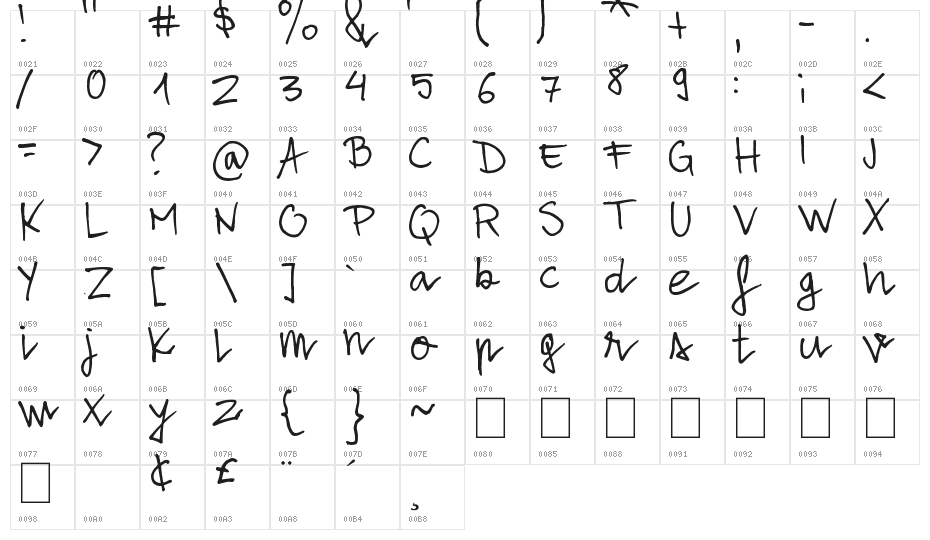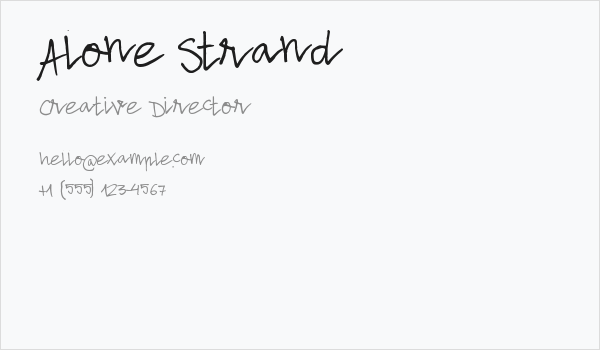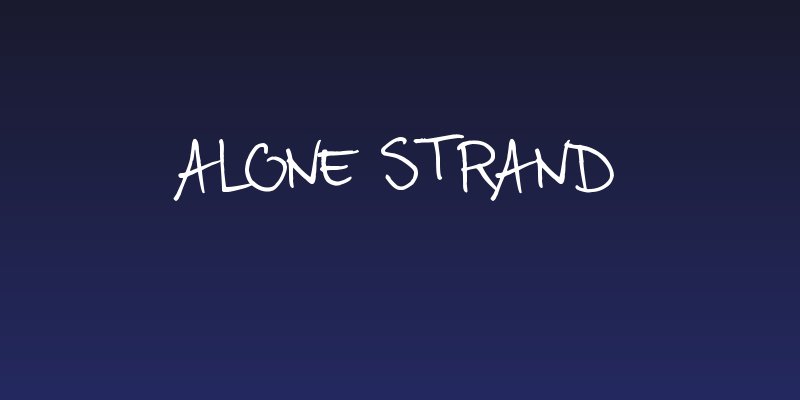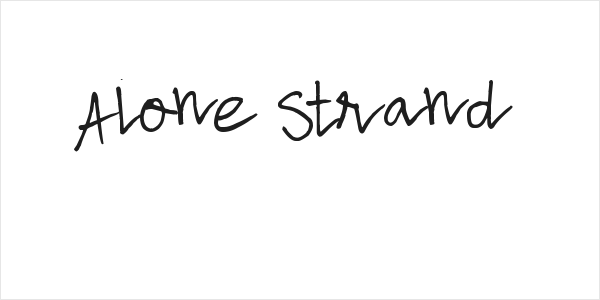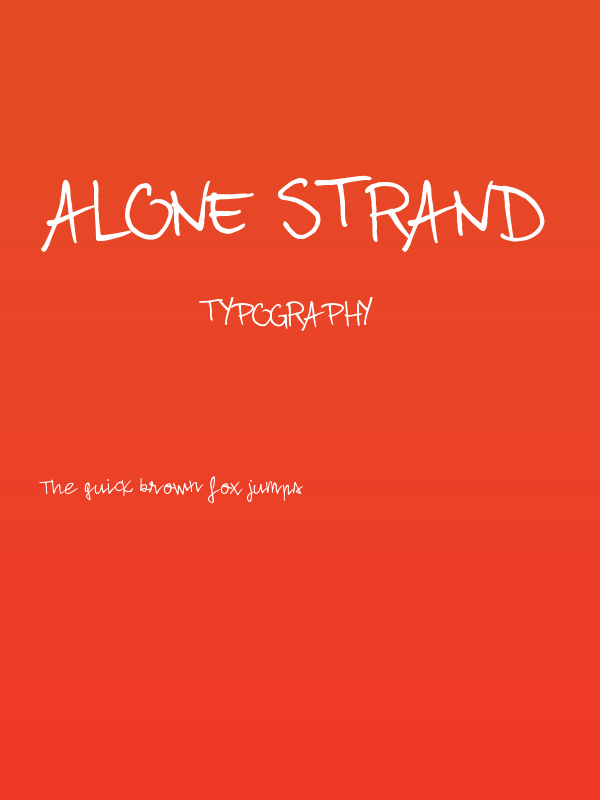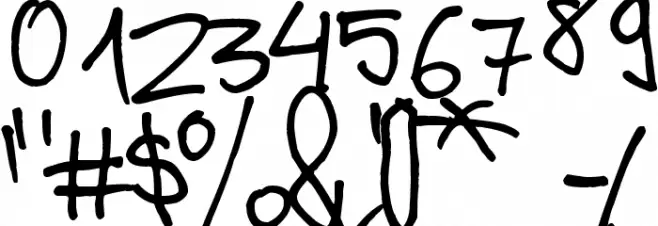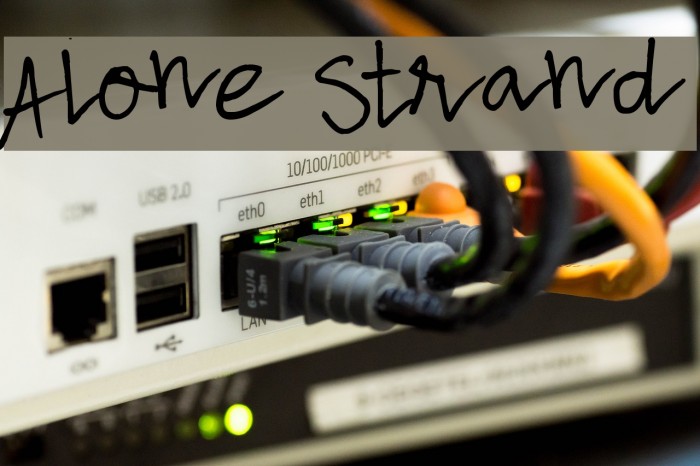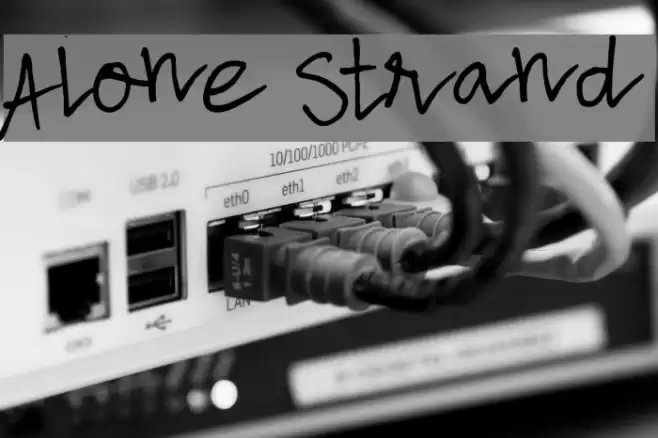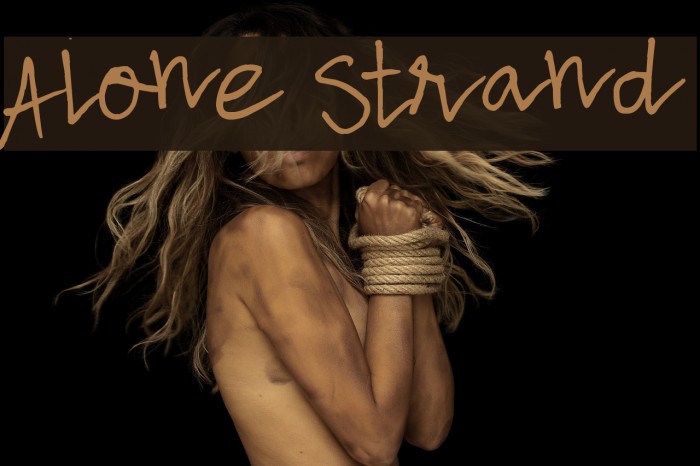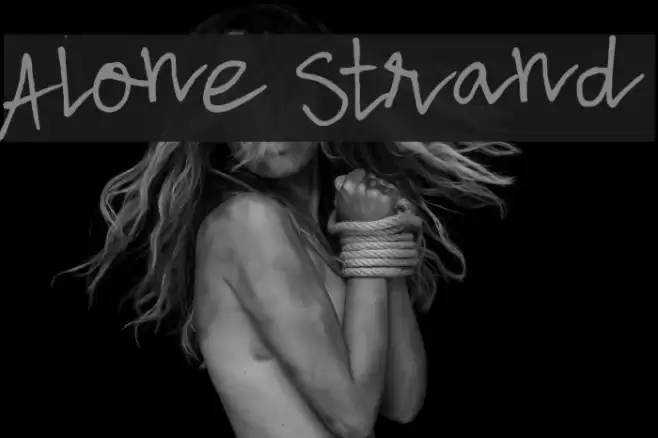
Alone Strand Font
| Общий стиль | Casual |
| Область применения | Logos, Greeting cards, Informal branding |
| Рекомендуемые проекты | Ideal for personal notes, greeting cards, casual branding, and creative projects that require a personal touch. |